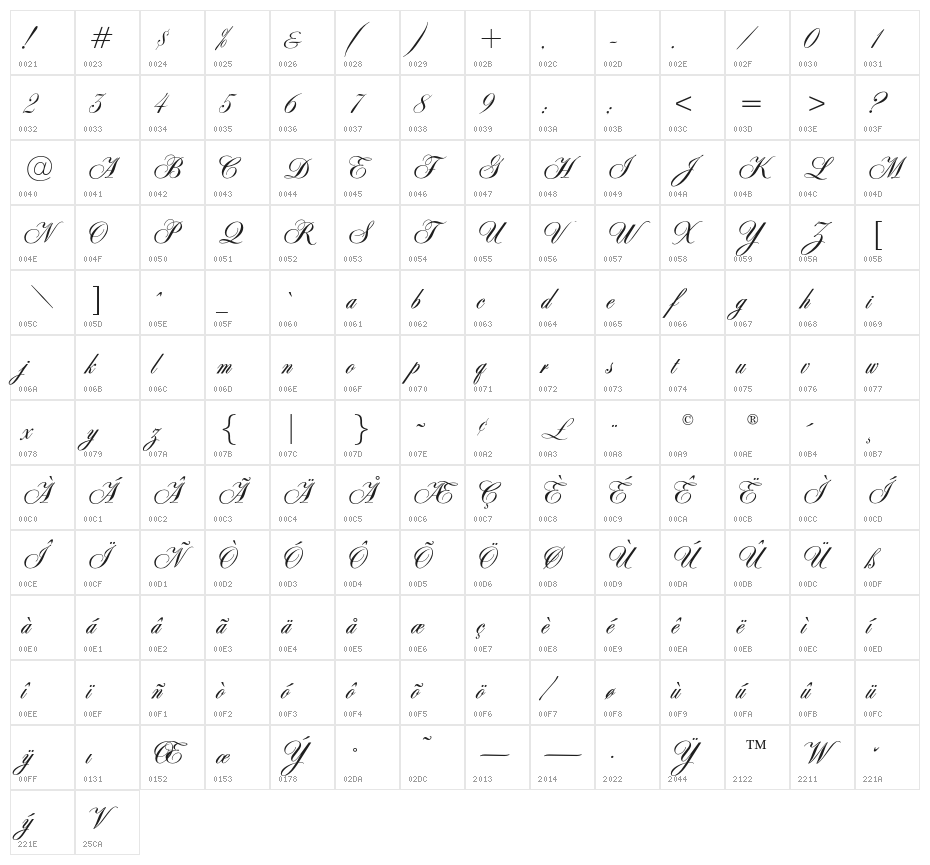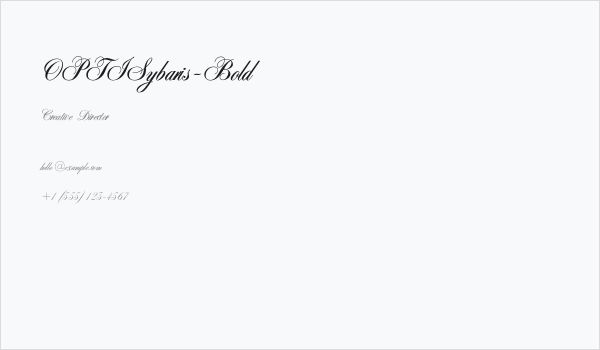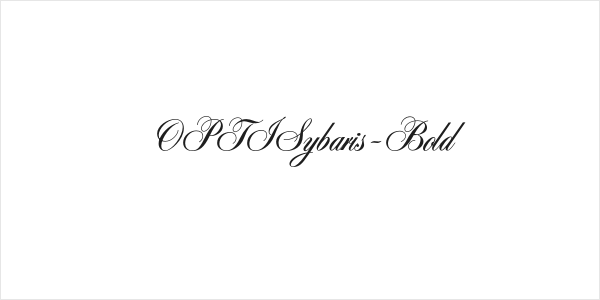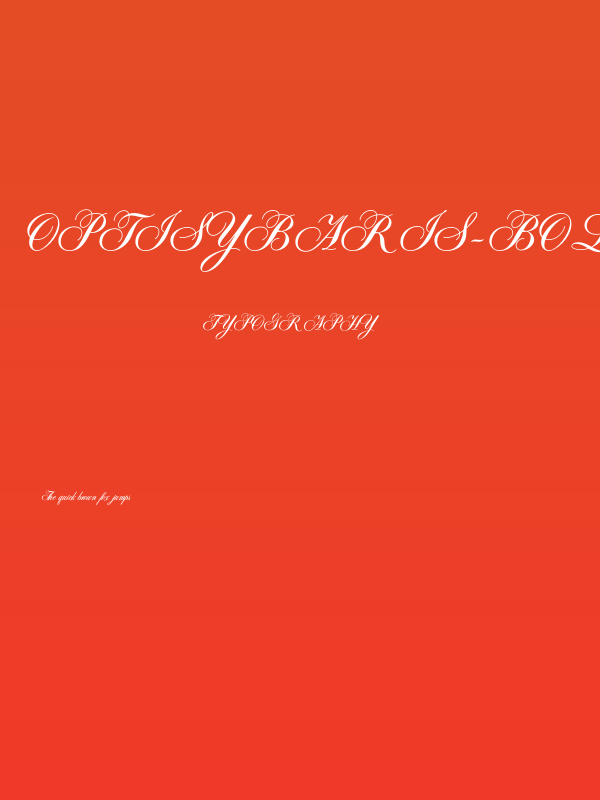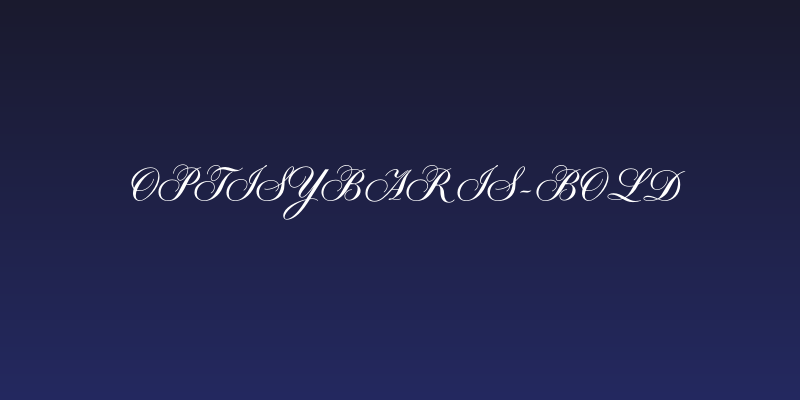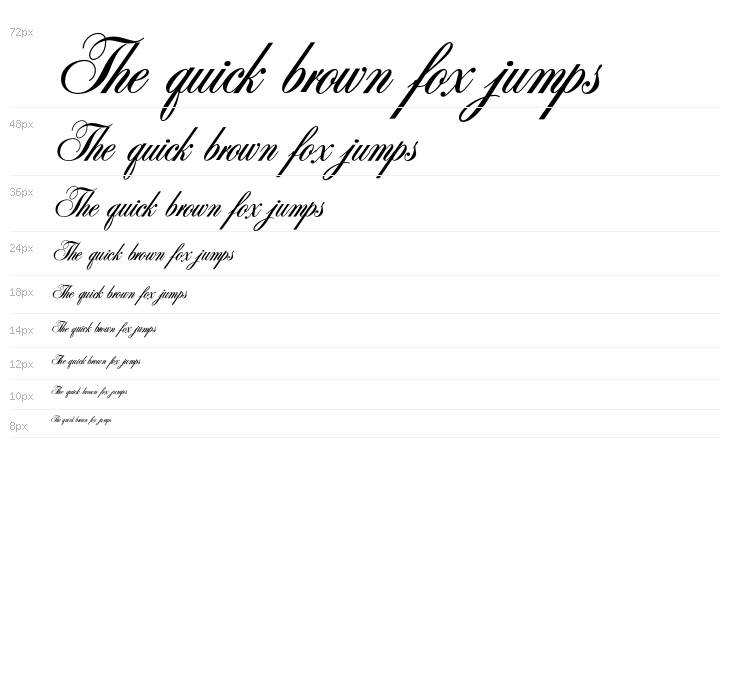
OPTISybaris-Bold Font
✎ Script
| Категория | Script |
| Общий стиль | Elegant, Formal, Decorative |
| Область применения | Headlines, Invitations, Branding |
| Рекомендуемые проекты | Ideal for wedding invitations, luxury branding, elegant signage, and formal event programs. |